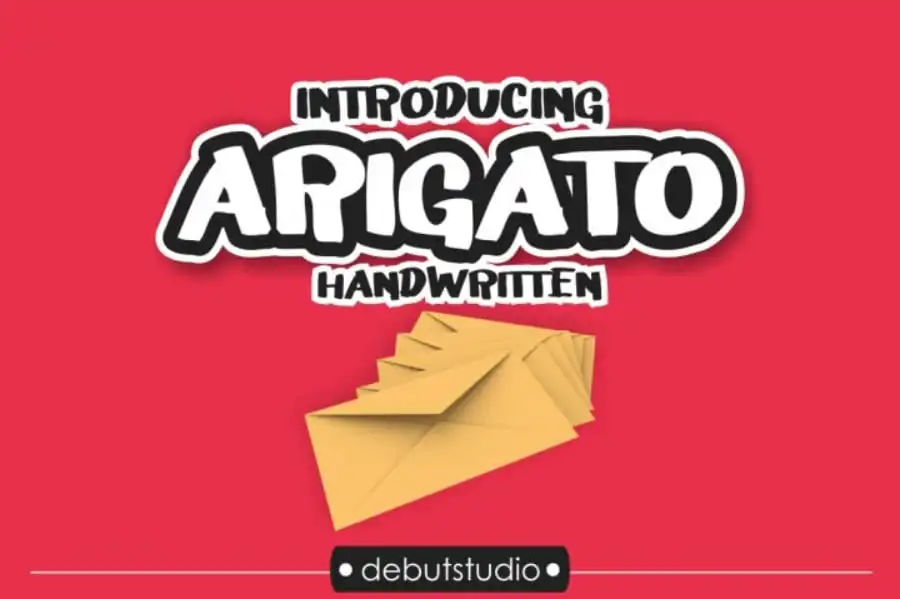
Introduzimos Arigato Font Handwritten Display. Desenhada pelo próprio 178-MC, é uma criação do designer Debut Studio. Este especializado no estilo display, foi criado a partir de suas próprias escritas manuscritas enviadas em envelopes. Ele considerou que essa caligrafia era perfeita para ser transformada em fonte para computador e está extremamente animado se você usar também. Com certeza vai adorar o charme único e a personalidade única desta fonte, combinando facilmente com estilos variados e textos de diferentes tamanhos.